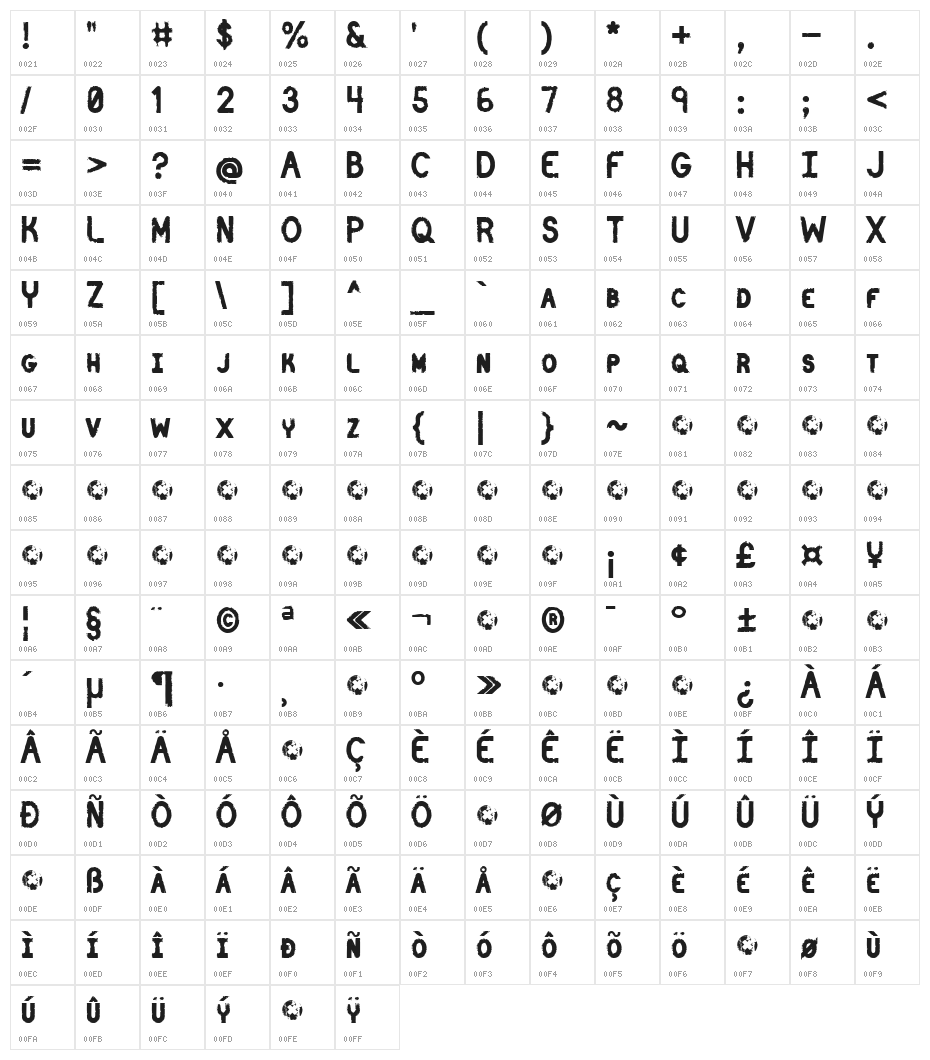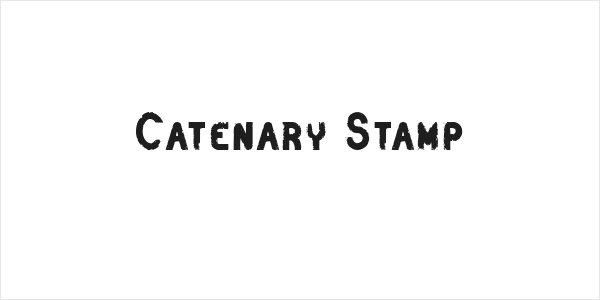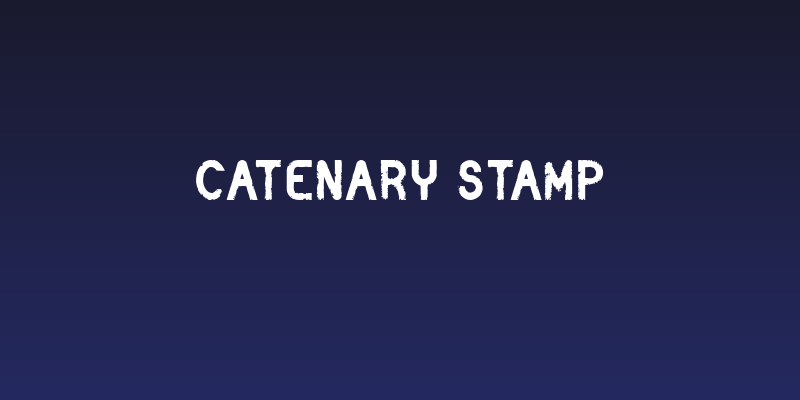
Catenary Stamp Font
| Categorie | Distorted Eroded |
| Stile generale | Industrial, Rugged |
| Progetti proposti | Ideal for posters, branding, packaging, and any design requiring a bold, industrial look. |